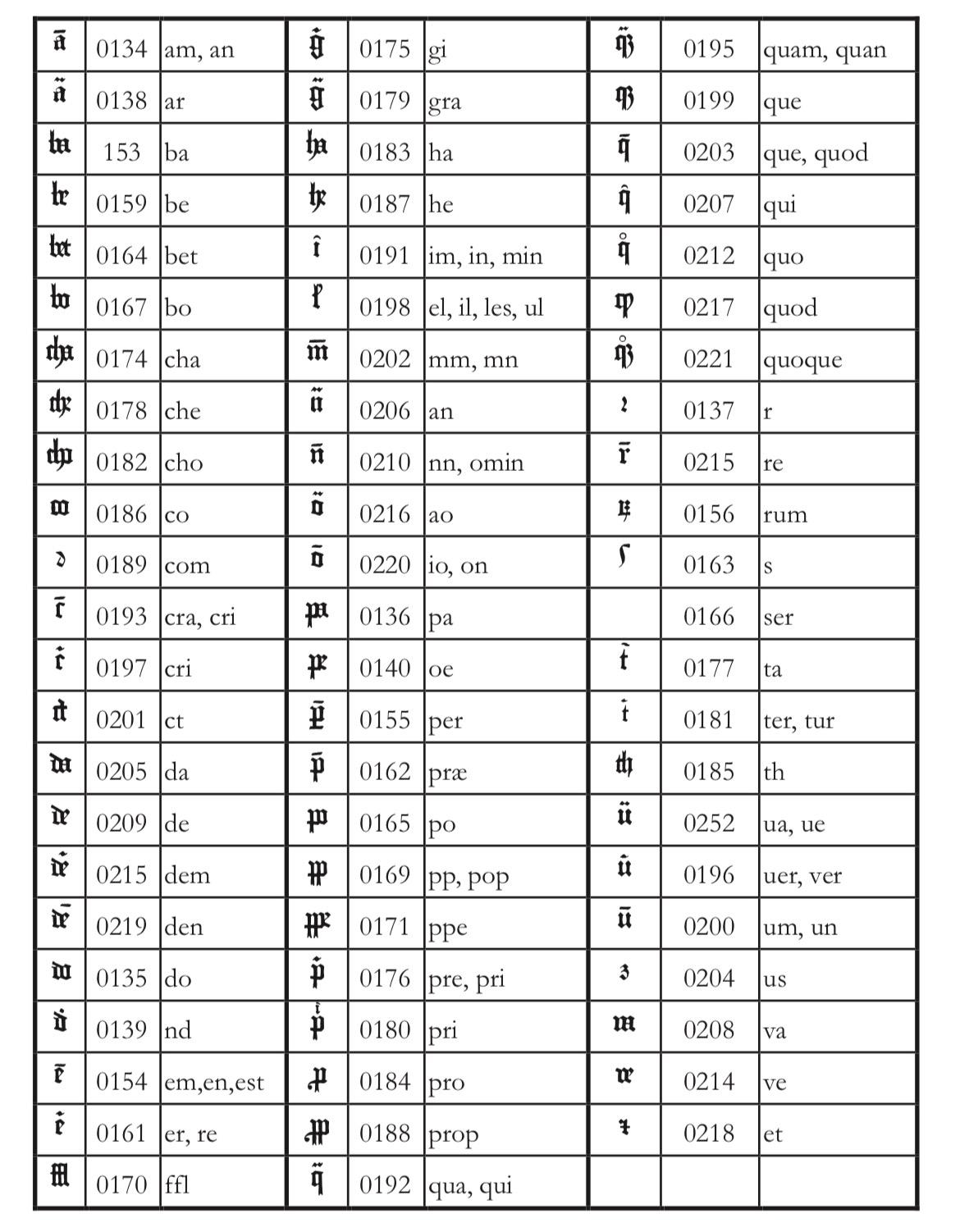
Zeichen der 42-zeiligen Gutenberg-Bibel
gibt es eine Übersicht aller in der 42-zeiligen Gutenberg-Bibel benutzten Zeichen nebst ihrer Varianten? Wenn ja, wo?
Auch wenn ich von der Foundry lange nichts mehr gehört habe, erinnere ich mich daran, dass die mal aus verschiedenen Gutenberg-Bibel-Auflagen Fonts machen wollten bzw. gemacht haben: alterlittera.com
@Norbert P Ich habe beim Gutenberg-Museum angefragt, konnte dort aber noch nichts erreichen; an die Gutenberg-Gesellschaft habe ich nicht gedacht (und an diese hat man mich beim Museum kurioserweise nicht verwiesen). – Die Übersicht sieht gut aus! Sie ähnelt dem, was auch den Einband des Bändchens „Johannes Gutenberg. Tatsachen und Thesen“ von Albert Kapr (Insel-Versalg 1977) unvollständig ziert, aber darin selber nicht zu finden ist.
@Oliver WeißAuch das sieht sehr gut aus!
@Phoibos Gutenberg B von Alter Littera habe ich, doch soweit ich weiß, wurden Zeichen hinzugefügt, die es im Original nicht gab (Paul Shaw spricht in „Revival Type“ von k und w, die hinzukamen, doch die sind auch dem Einband des Bändchens von Albert Kapr zu sehen). – Ich weiß natürlich, dass es nicht den einen Font gab, sondern die Zeichen überarbeitet und bestimmt auch ergänzt wurden.
Es gibt im Taschen-Verlag eine Faksimile-Ausgabe der Gutenberg-Bibel.
Dieser Ausgabe ist ein zusätzliches Buch von Stephan Füssel mit vielen Informationen zur Gutenberg-Bibel beigelegt. Unter anderem mit zahlreichen Links zu frei verfügbaren digitalen Editionen der Gutenber-Bibel weltweit.
doch die sind auch dem Einband des Bändchens von Albert Kapr zu sehen
Das kann ein Zirkelschluss sein, da:
The main historical sources used during the font design process were high-resolution scans from several printings of Gutenberg's Bible. Other sources were as follows: Kapr, A. (1996), Johann Gutenberg - The Man and his Invention, Aldershot: Scolar Press (ch. 7); De Hamel, C. (2001), The Book - A History of The Bible, London: Phaidon Press (ch. 8); Füssel, S. (2005), Gutenberg and the impact of printing, Burlington: Ashgate (ch. 1); and Man, J. (2009), The Gutenberg Revolution, London: Bantam (ch. 7).
Um diese Frage final beantworten zu können, müssten alle Seiten aller auf uns gekommener Fragmente, Teile und vollständiger Exemplare gesichtet werden. Oder wir vertrauen Kapr.